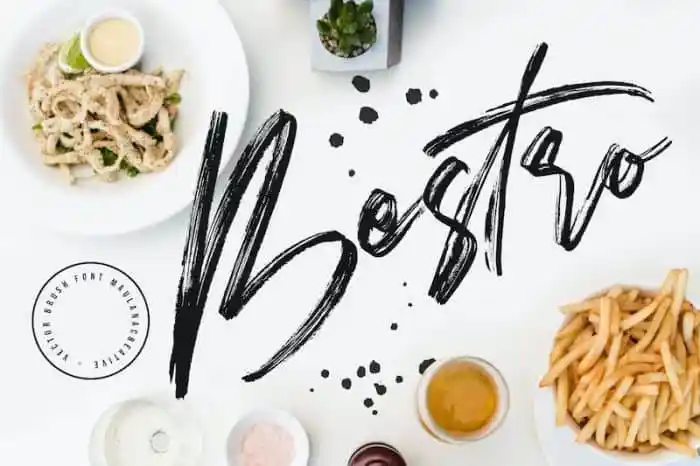
Bestro Brush Font – Download Grátis
A Bestro Brush Font é uma delicada tipografia desenhada a mão com traços suaves, criada especialmente para uso em projetos de embalagens. Seu design elegante foi pensado para estilizar elementos como rótulos e marcas, tornando-os mais enigmáticos e envolventes. Essa fonte é perfeita para uma variedade de aplicações, incluindo identidade visual, camisetas personalizadas, postagens nas redes sociais, anúncios, embalagens de produtos, designs de produto, etiquetas, marca d’água e cartões de convite. Ela também é ideal para qualquer projeto que você precise estilizar e dar um toque acentuado, seja em uma camiseta customizada ou em um post nas redes sociais. Criada pelo Maulana Creative na plataforma 99designs, a Bestro Brush Font oferece os detalhes perfeitos para personalizar sua marca de forma única. Suas curvas suaves e suas formas delicadas criam uma atmosfera agradável e envolvente que certamente será adorada por designers gráficos e marqueteiros buscando estilos únicos e envolventes em suas criações.